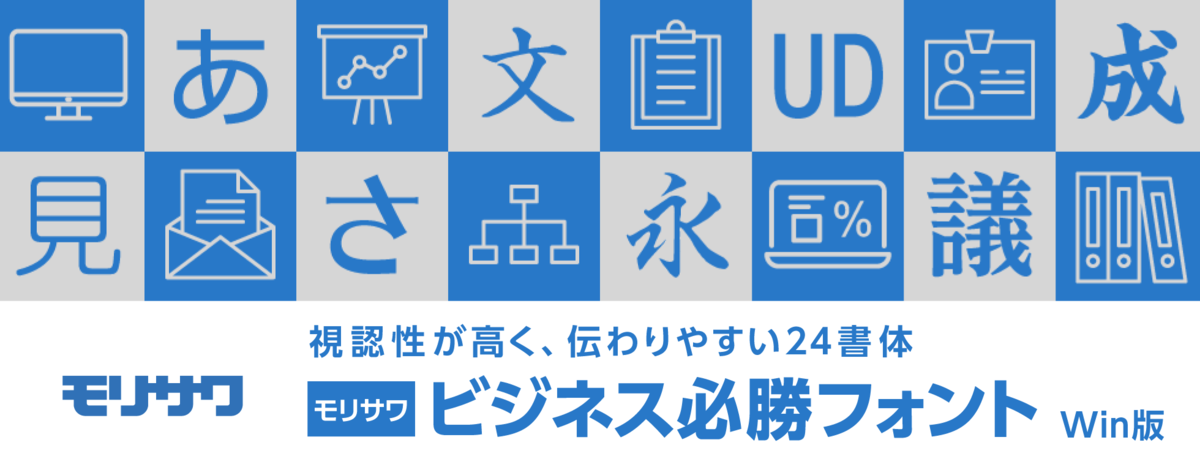
モリサワ「UDフォント」などビジネスに役立つフォントを収録したライセンスパッケージをソースネクスト・サイトで発売
モリサワは、2025年2月27日から、ビジネスシーンにおけるドキュメントやコンテンツ作成に役立つフォントを収録したライセンスパッケージ「モリサワ ビジネス必勝フォント Win版」を、ソースネクストの運営するソースネクスト・サイトで発売を開始した。
「モリサワ ビジネス必勝フォント Win版」は、弱視や老眼の方なども含むより多くの人に読みやすいように開発されたモリサワのUD(ユニバーサルデザイン)フォントに、挨拶状・賞状・履歴書・領収書などの礼節が必要な場面で役立つ楷書・行書体フォント合計24書体を収録。
読みやすいフォントでしっかり情報を伝えたい、差別化を図りたいビジネスパーソンの人におすすめのラインナップとなる。
▼搭載書体